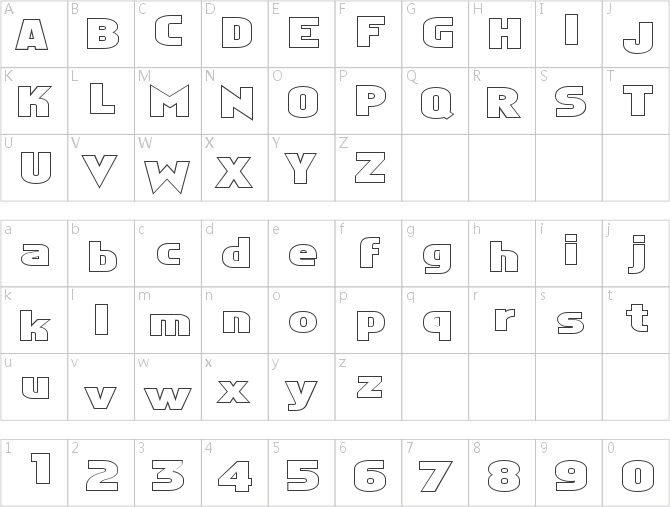
FZ BASIC 5 HOLLOW EX
FZ BASIC 5 HOLLOW EX介绍
FZ BASIC 5 HOLLOW EX字体字库是一款让人赏心悦目、百看不厌的英文字体,适合各类广告和产品包装设计应用,字体大小0.07MB,格式为ttf字体,上传用户是哼哼哈兮,作者/版权方为未知
FZ BASIC 5 HOLLOW EX效果图